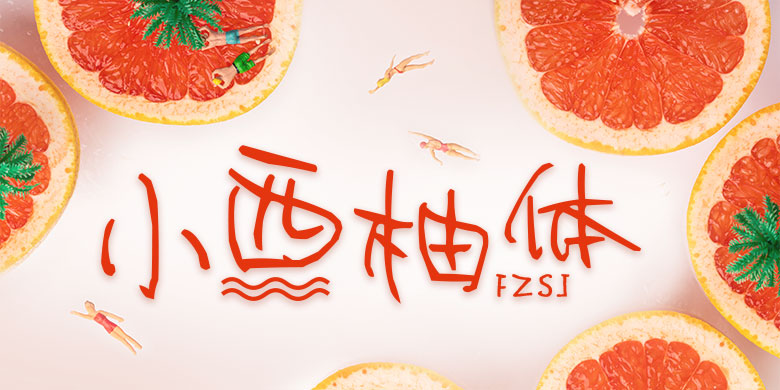
方正手迹-小西柚体
字体品牌: 方正手迹 设计师:黄少雄 字体分类:创意书写 字体属性:精品字 字符集:大陆简体(GB2312-80) 发布时间: 2019
方正手迹-小西柚体大胆采用了左高右低的字形特点,极具动感。笔画设计自由度较高,灵活多变,使小西柚体灵动飘逸,极具特色。适用于文化类的宣传设计,以及商业类品牌的广告和产品包装设计。